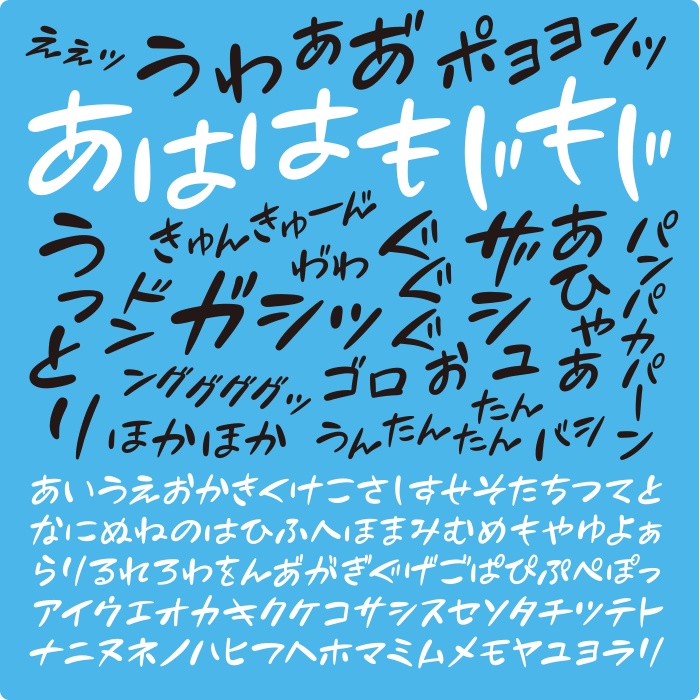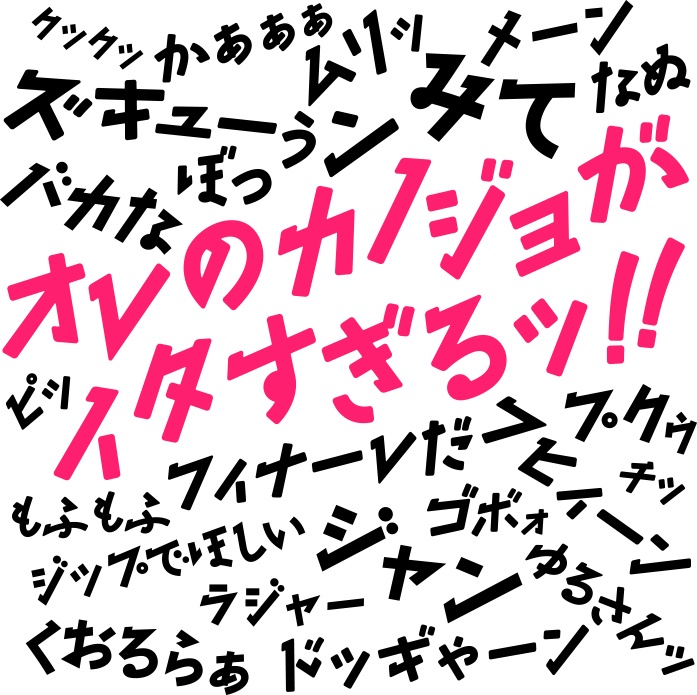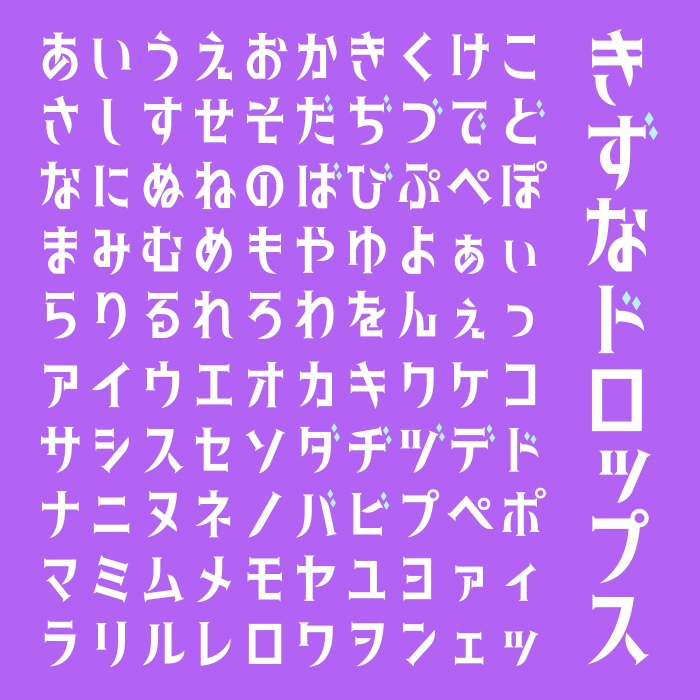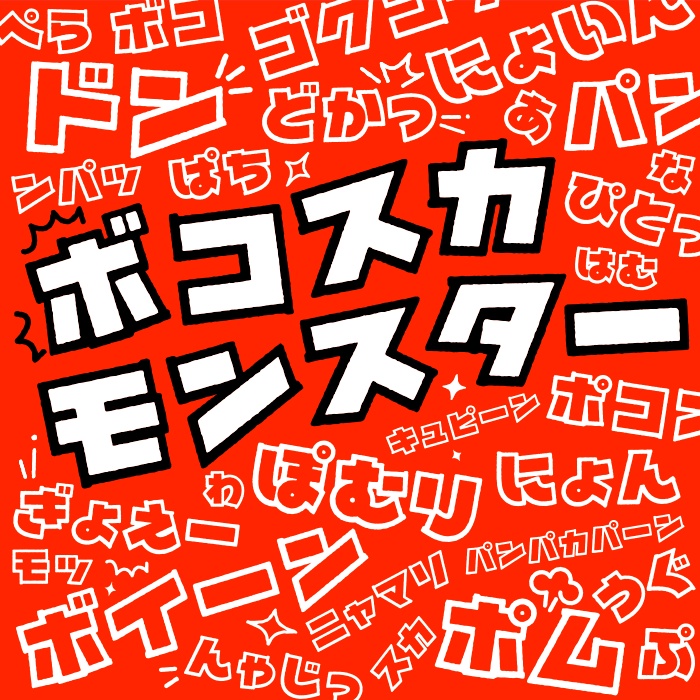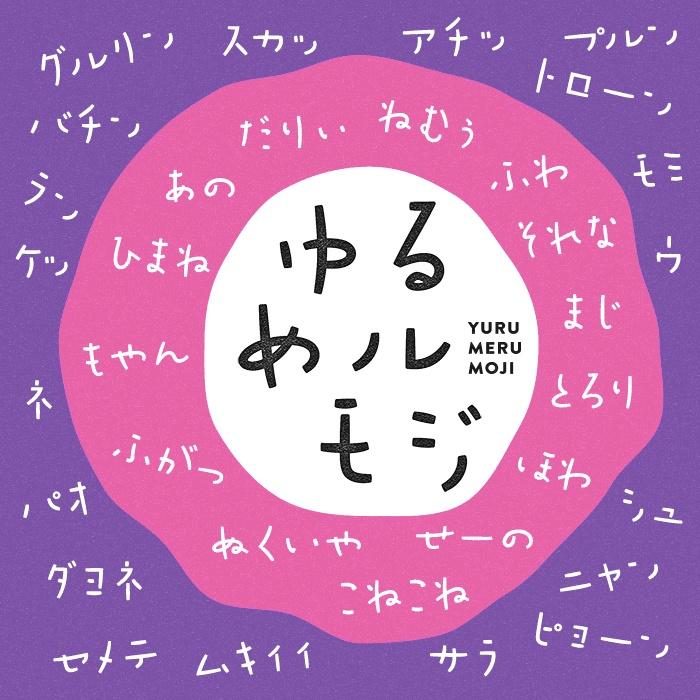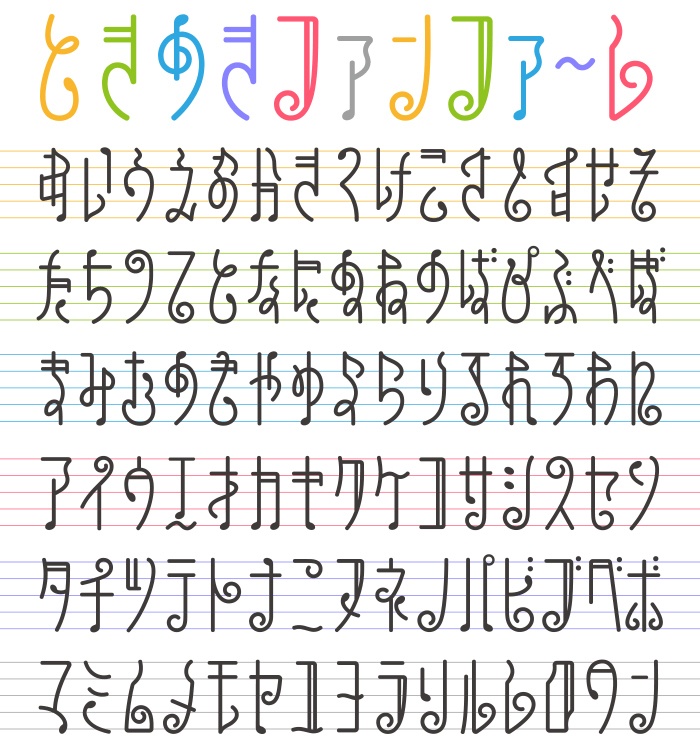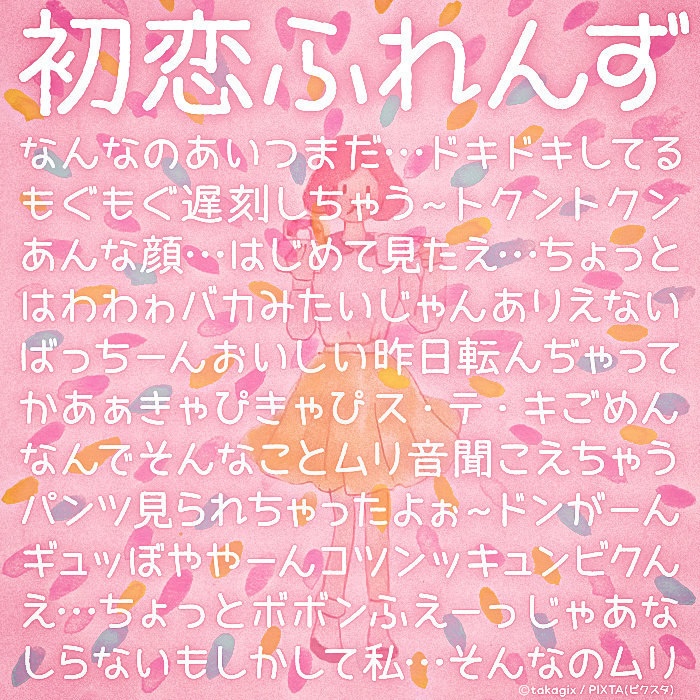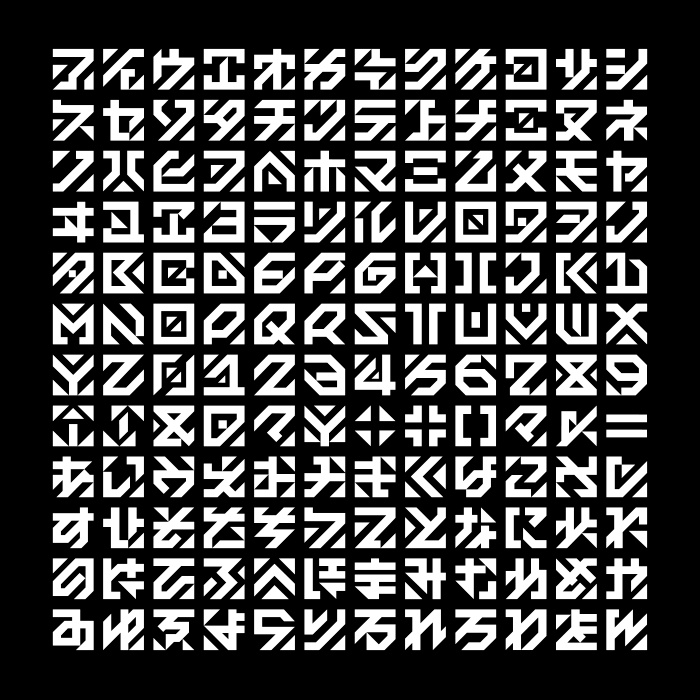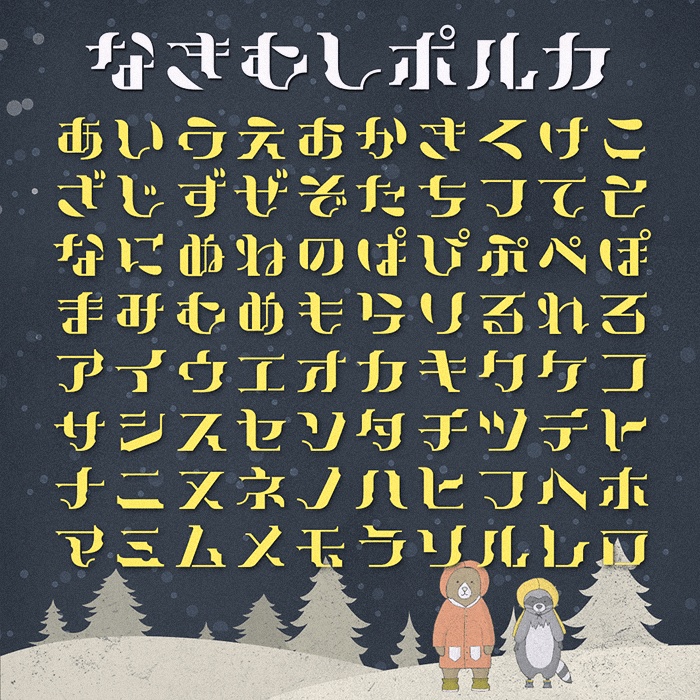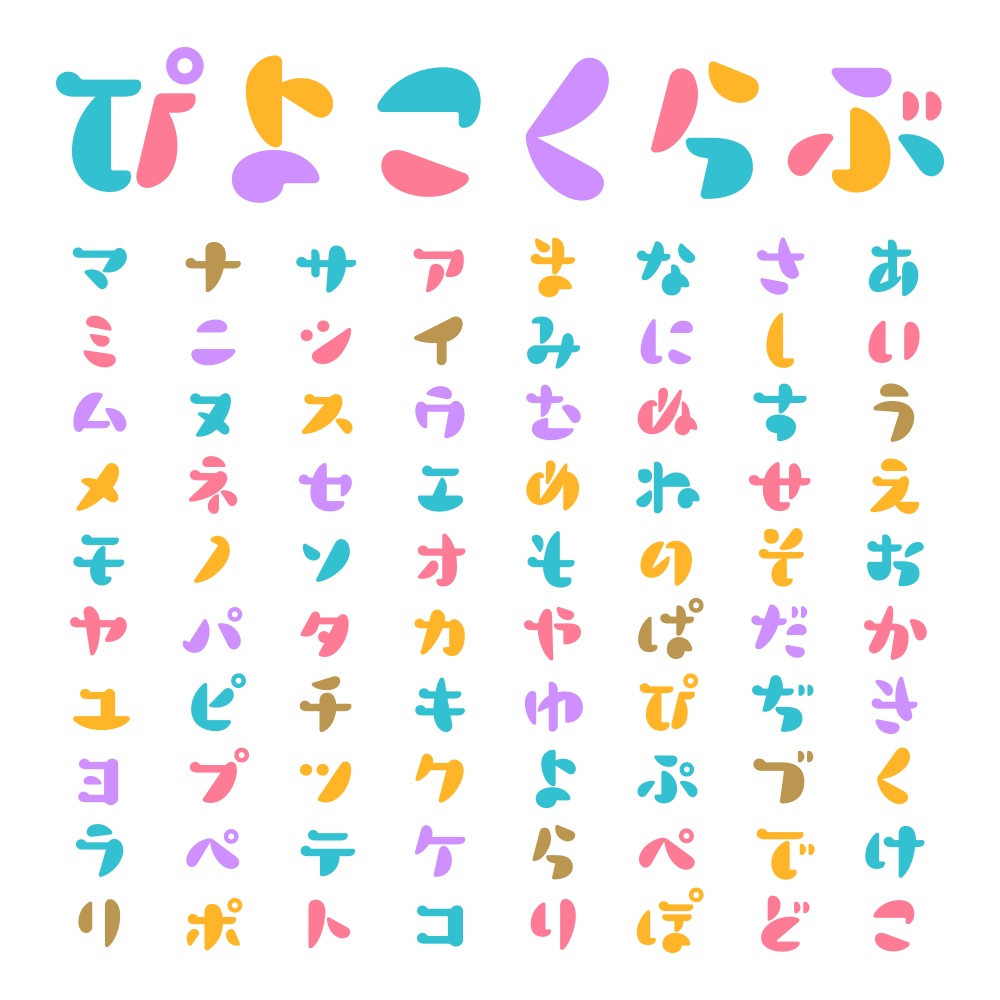
フォントオノマトペ 28フォント収録
フォントオノマトペ 擬音・擬態語にぴったりのフォント集 ひらがな・カタカナのオノマトペに注目した日本語フォント集のダウンロード販売。擬音語・擬態語にぴったりのユニークなフォントは、漫画だけでなく幅広い用途に使えるようにデザインされています。安心して使える商用利用可のオリジナルフォント集です。今後追加されるフォントのアップデートは無料です。 収録文字 ひらがな・カタカナ ※初恋ふれんずのみ収録文字数4,072文字(第一水準2965文字+第二水準460文字+ひらがな、カタカナ、約物、記号、アルファベット等647文字) 収録フォント あははもじもじ、オレのカノジョがイタすぎる春 、オレのカノジョがイタすぎる夏、オレのカノジョがイタすぎる秋、オレのカノジョがイタすぎる冬、きずなドロップス-なみだ、きずなドロップス、ボコスカモンスター、ボコスカモンスターつちぞくせい、ボコスカモンスターかぜぞくせい、ボコスカモンスターみずぞくせい、ボコスカモンスターひかりぞくせい、ボコスカモンスターこおりぞくせい、ボコスカモンスターひぞくせい、ゆるめルモジ、ゆるめルモジてがき、ときめきファンファーレ、どれみファンファーレ、初恋ふれんず、インビジブル、なきむしポルカ、なきむしポルカシャープ、なきむしポルカラウンド、ぴよこくらぶ、ぴよこくらぶ-よみやすい、ぴよこくらぶ-しゃたい、カフカヘンType1、カフカヘンType2 動作環境 Mac:OS X対応(10.x)以降 Windows:OS/日本語版Windows XP、VISTA、Windows7〜11以降 フォント形式:OpenType 安心して使えるロイヤリティフリーの書体 あらゆる商用・デザイン用途(印刷物・ゲーム・アプリ・映像・動画・ロゴ・同人作品)に使用できる、商用申請の必要のないロイヤリティフリーの書体になります。文字の加工・変形も可能です。ご安心ください。 1商品(1ライセンス)につき1ユーザー1PCのみがご利用いただけます。複数人で使用する場合は人数分をご購入ください。